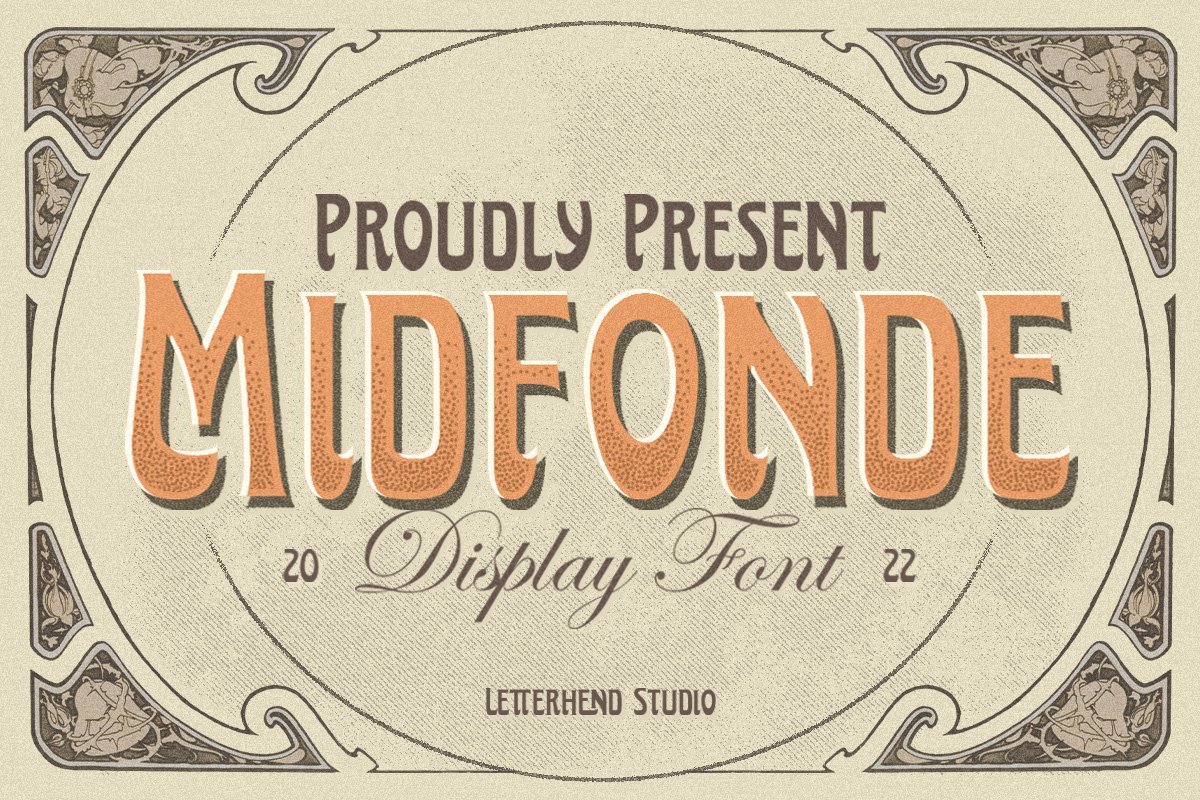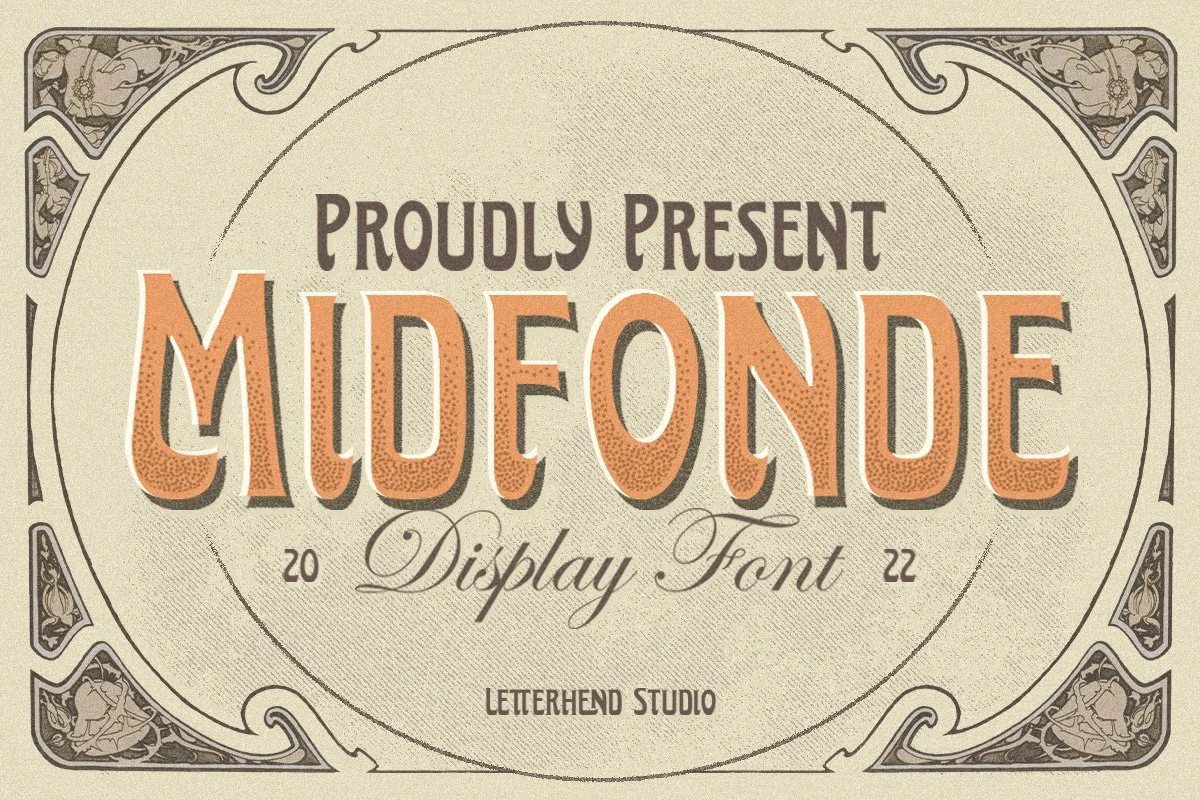
[Fontbundles] Midfonde - Display Font (2022)
Midfonde - это шрифт, вдохновленный стилем арт-деко. Этот тип шрифта идеально подходит для использования в логотипах, заголовках, вывесках и других различных формах, таких как приглашения, этикетки, логотипы, журналы, книги, поздравительные / свадебные открытки, упаковка, мода, макияж, канцелярские принадлежности, романы, этикетки или любые рекламные цели.